Nhà văn người Canada - Kevin Chong đã khảo sát quan điểm về font chữ của một nhóm tác giả.
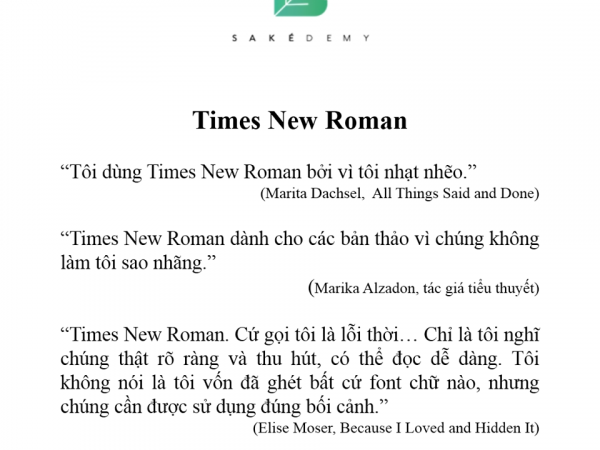
Như một thói quen: Bật Word, chọn mục Font và gõ "Times New Roman". Có ai giống tôi không?
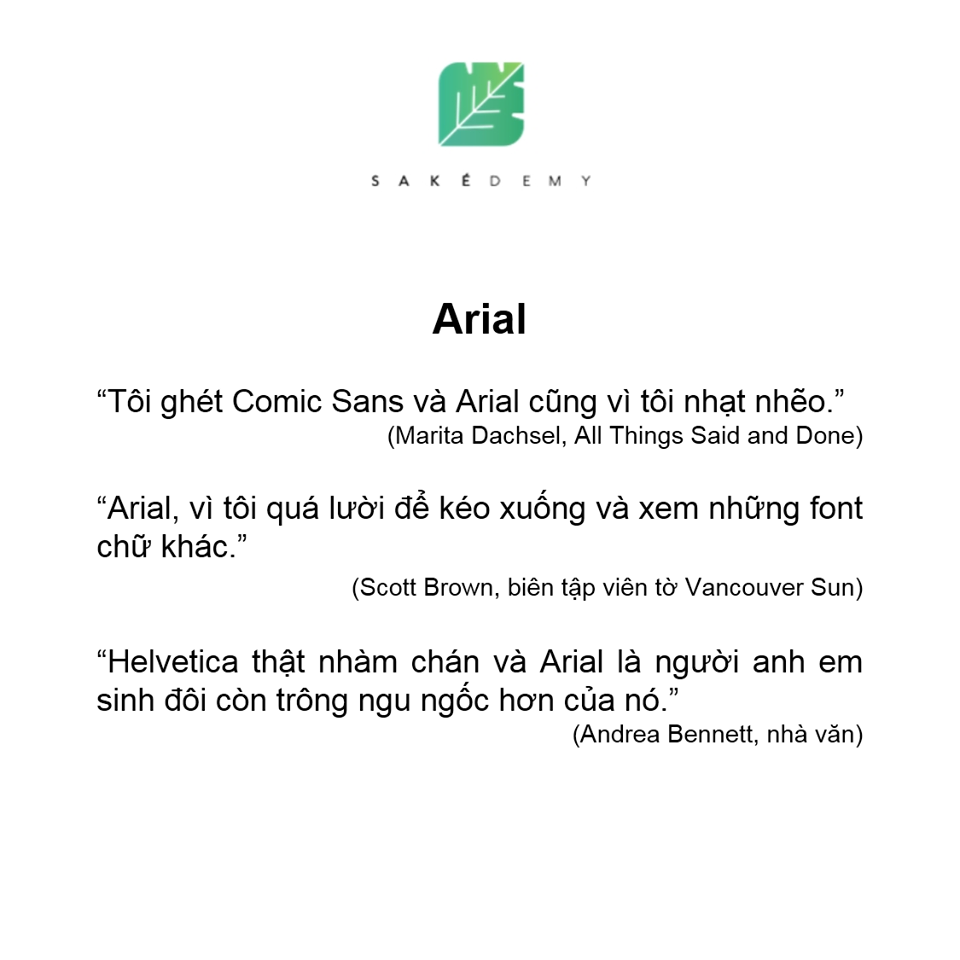
Lí do thì chỉ có một: Lười. Cái lợi thế của font có chữ cái đầu tiên trong bảng kí tự đó, đỡ phải tìm.
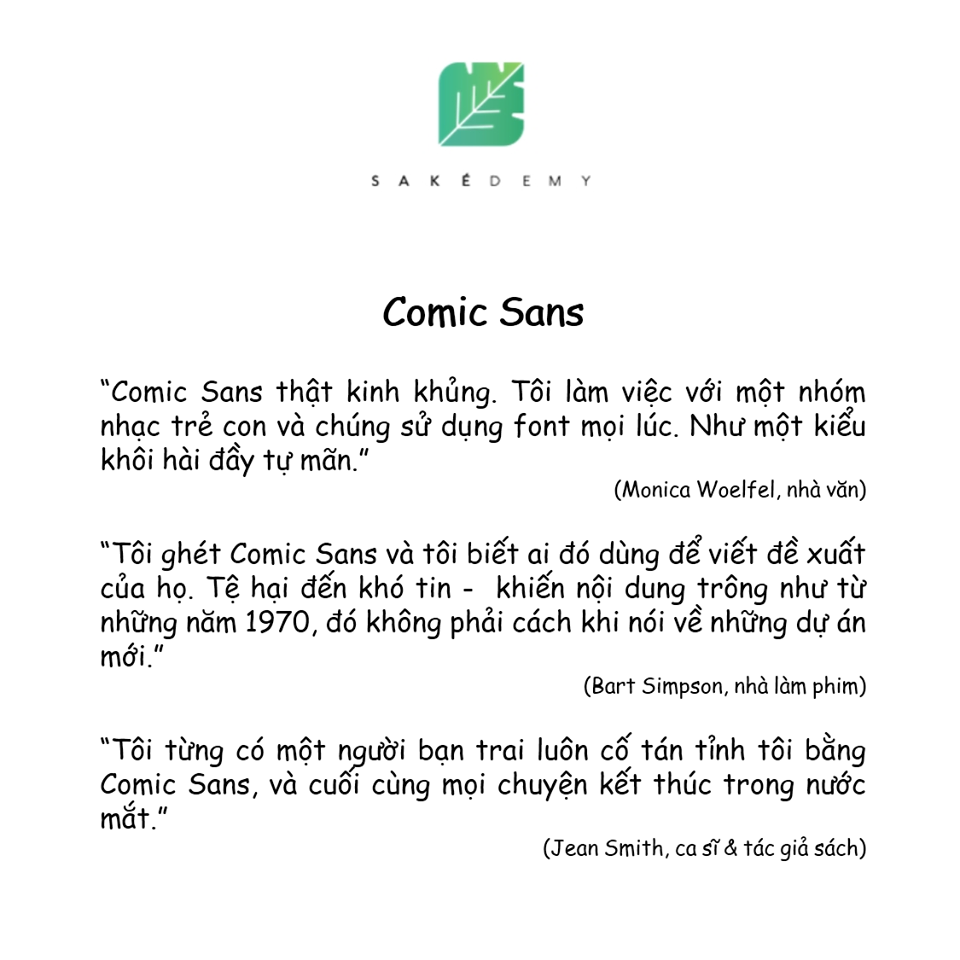
Tip quan trọng nhất định bạn phải nhớ: Đừng bao giờ dùng font Comic Sans để viết thư tình, không bạn sẽ phải hối hận!
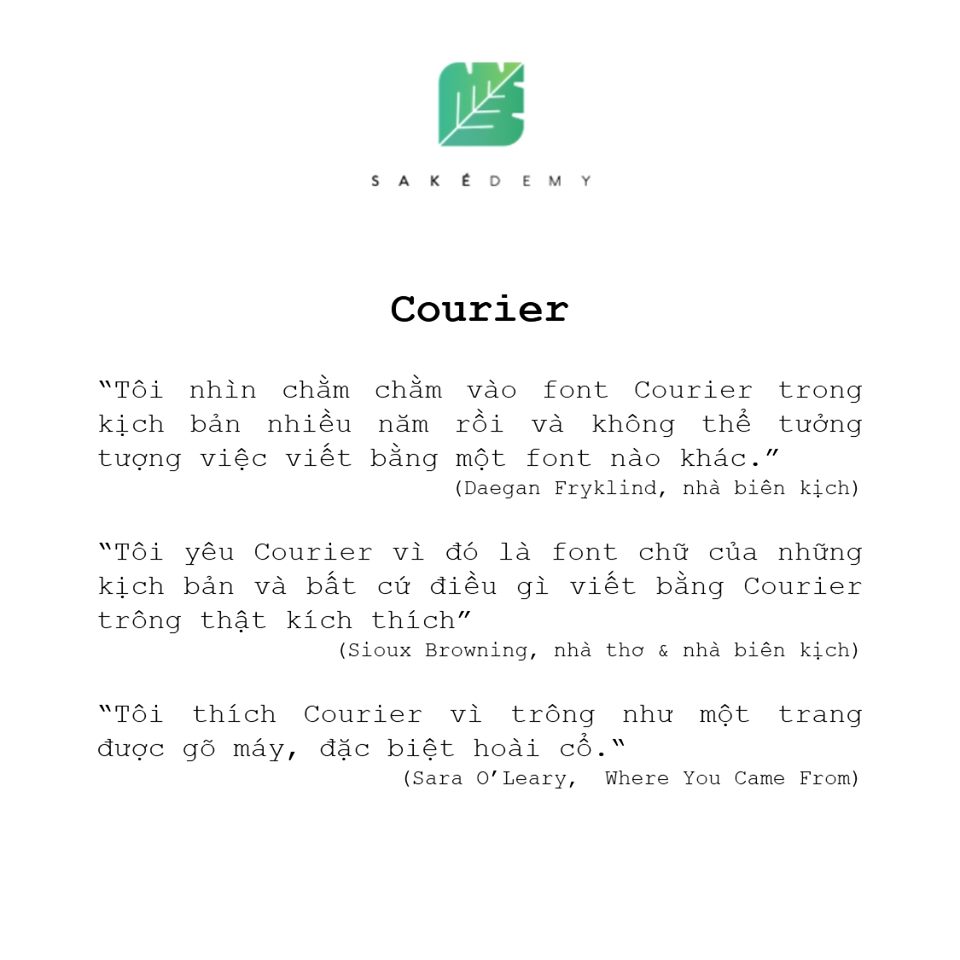
Những người sử dụng Courier là tập hợp những người khó tính, đã quá quen chỉ sử dụng độc nhất một font chữ.
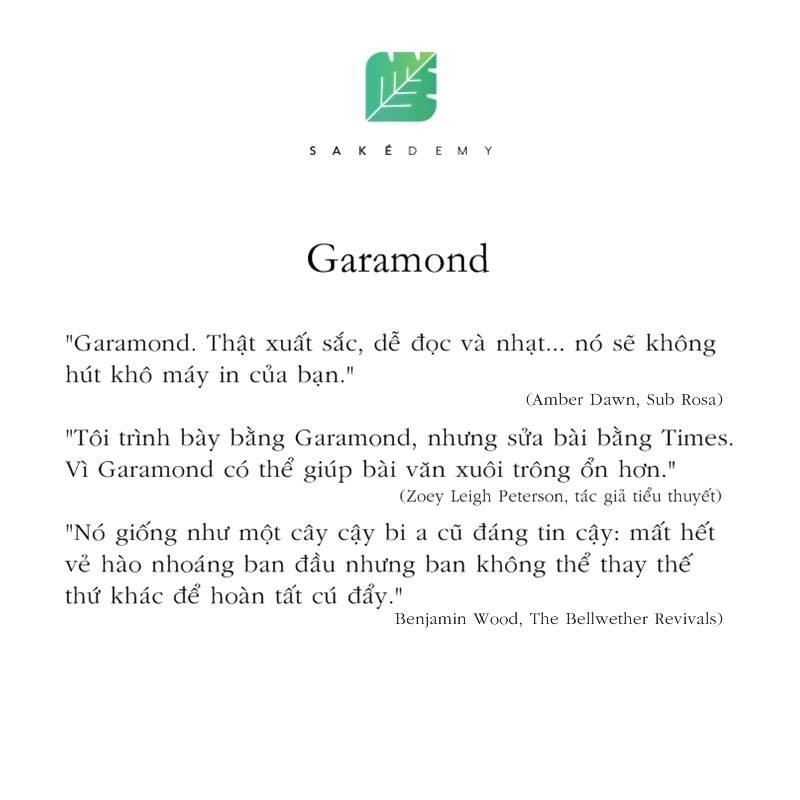
Ai đọc sách tiểu thuyết lãng mạn thường xuyên sẽ bắt gặp "người quen" này!
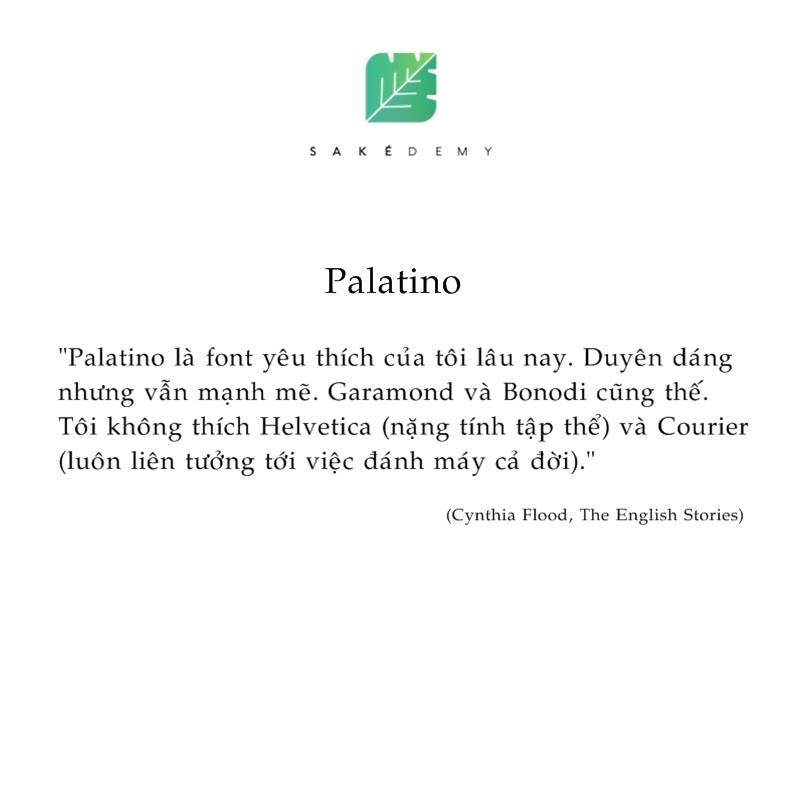
Thêm một font quen thuộc của hội "mọt sách", nhưng quan trọng là, tôi sử dụng nó thường xuyên vì tôi... thích thế!
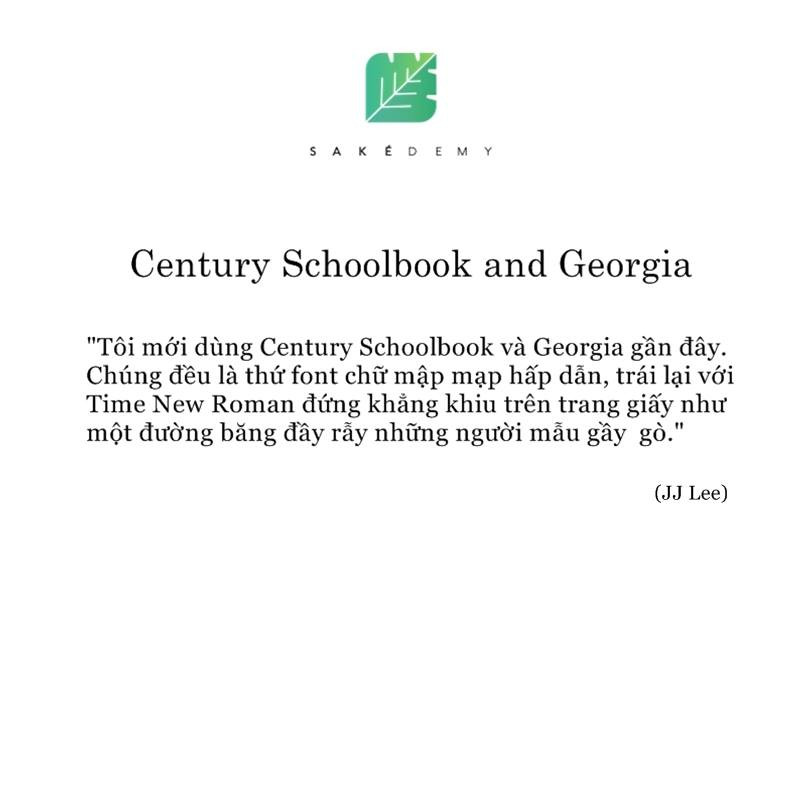
Mập mạp nhưng tấp nập người mê!
Vậy đâu là font chữ hay sử dụng của bạn?